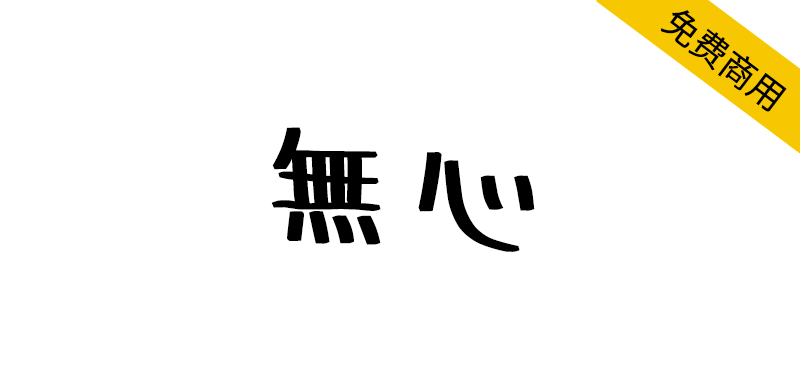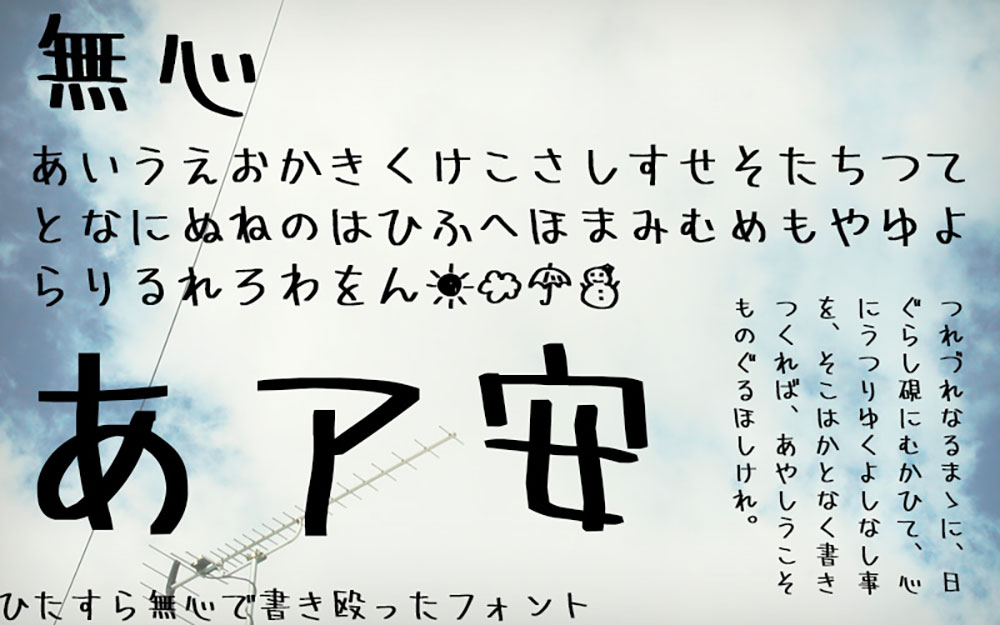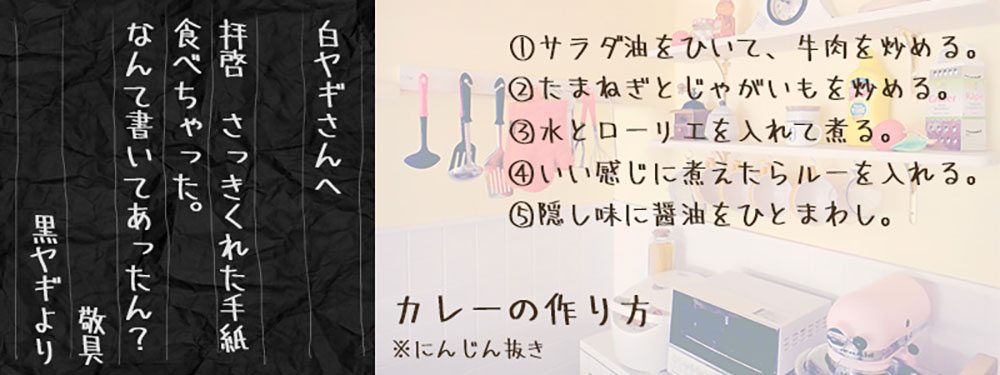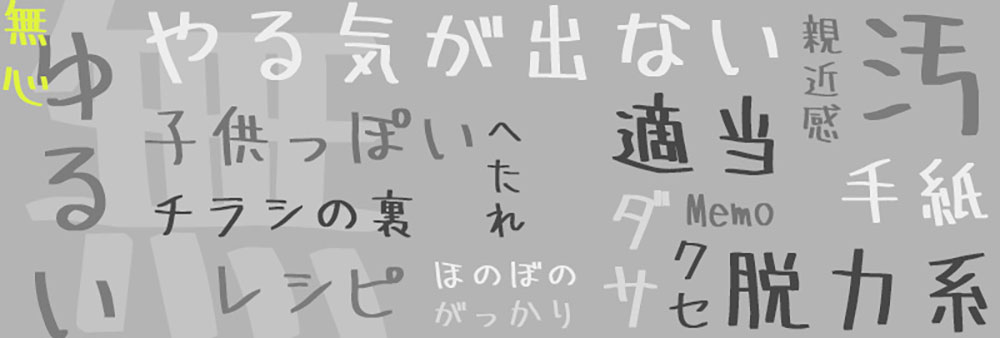
【無心】一种没有任何主题概念,随意书写的日文字体
这只是我没有经过思考就写出来的手写字体。这只是作者的写作,没有任何主题或概念。因为相当粗糙,所以小尺寸使用可能比较好。
ただひたすら無心で書き殴った手書きフォントです。何のテーマもコンセプトもない、ただの作者の字です。かなりザクザクしているので、小さめサイズで使うのがいいかもしれません。